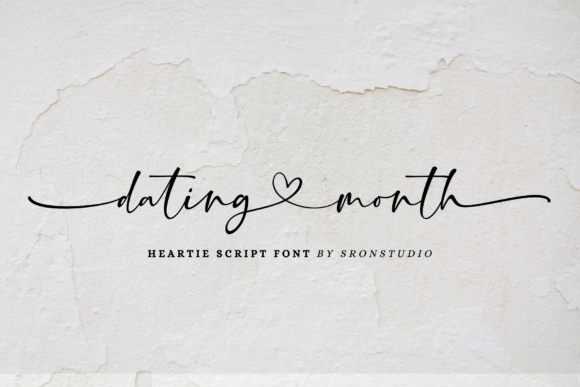
Dating Month
Se você está procurando ativos de alta qualidade como Dating Month, este pacote premium é uma escolha fantástica para seus projetos criativos.
Trabalhado com precisão, Dating Month fornece vetores limpos, tipografia suave e uma licença comercial para sua tranquilidade.
Quer você esteja criando produtos POD (Print on Demand), convites de casamento ou gráficos para mídias sociais, Dating Month é a escolha ideal.